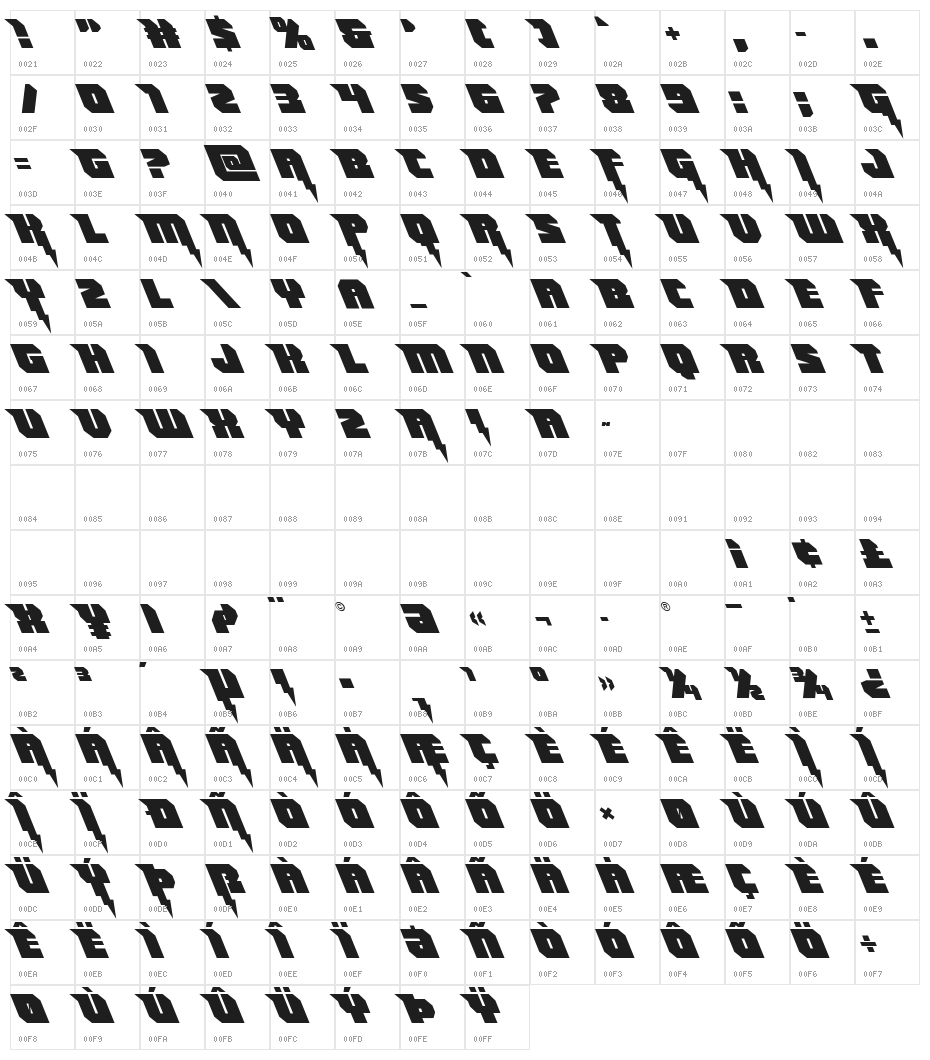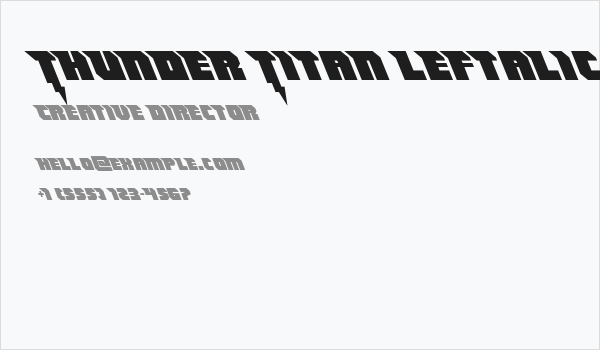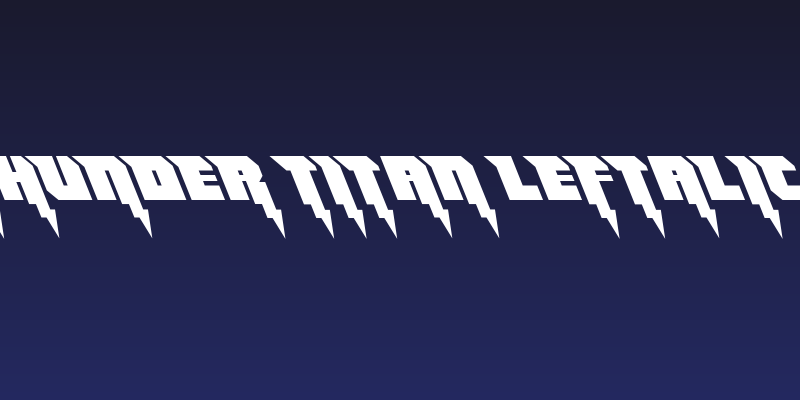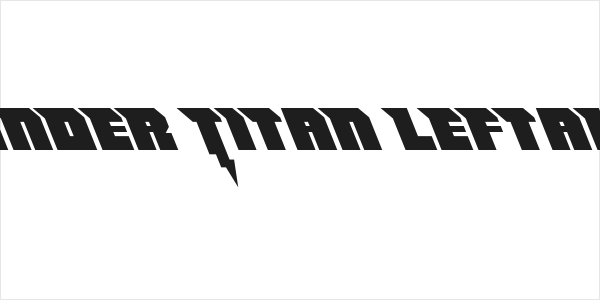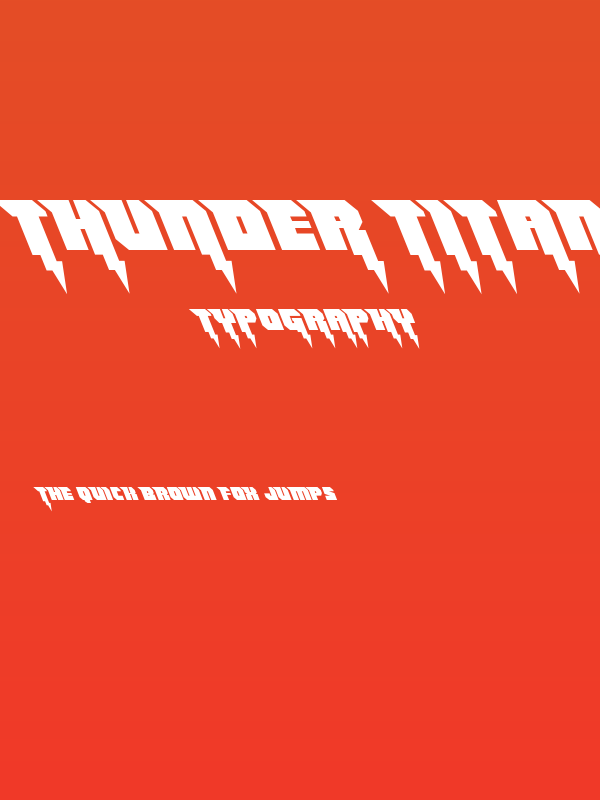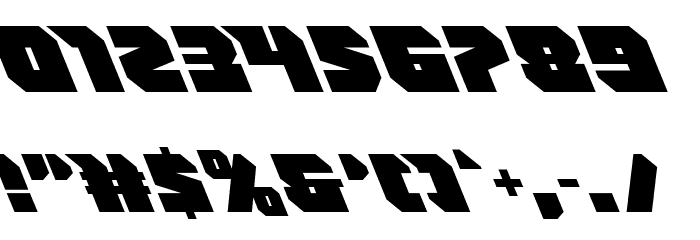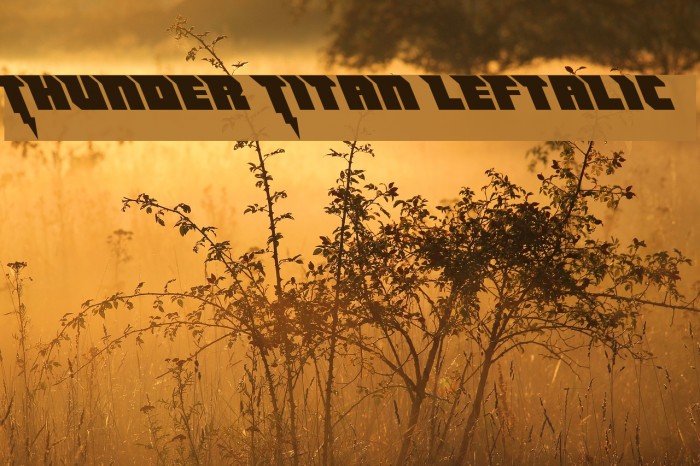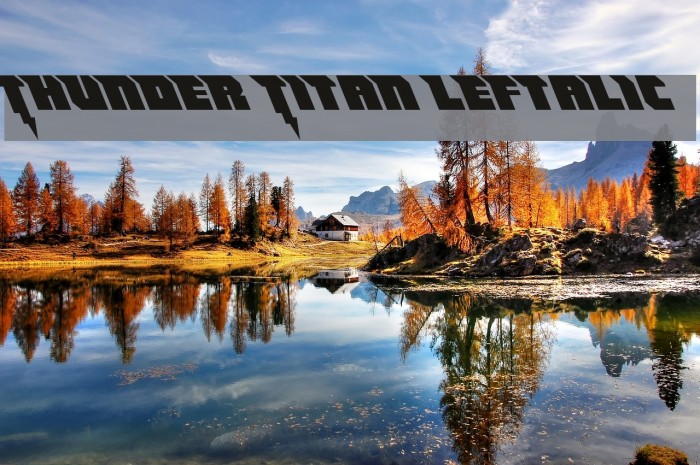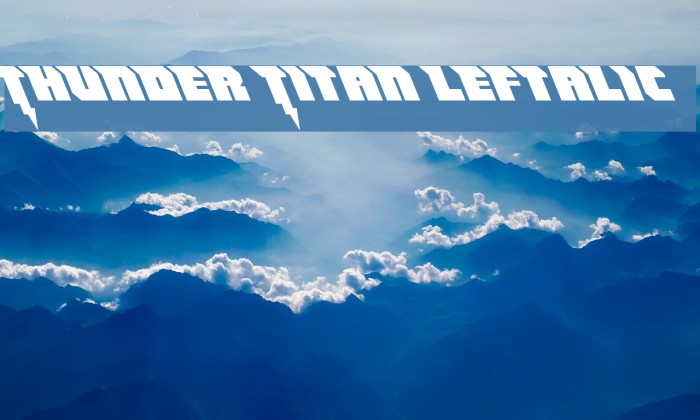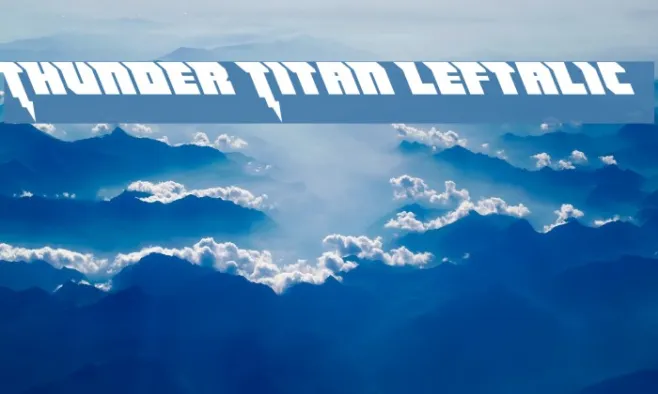
Thunder Titan Leftalic Font
| Proyectos propuestos | Ideal for sports branding, action movie posters, video game titles, and any project needing a powerful, energetic aesthetic. |